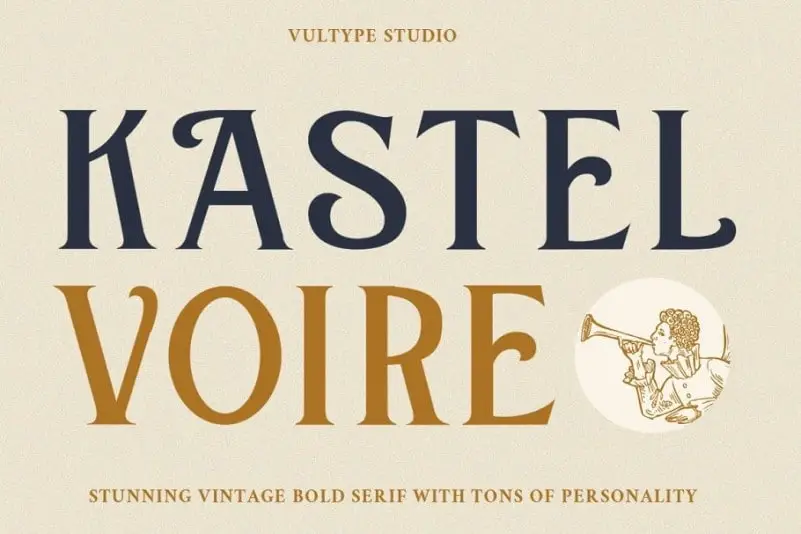
Kastel Voire Serif Font – Download Grátis
A Kastel Voire Serif é uma fonte serif display moderna que se destaca perfeitamente para criações visuais como logomarcas, identidades corporativas e cabeçalhos de sites. Com sua aparência minimalista e contrastes sutis, essa font foi projetada pela Vultype Co. e inspirou-se na estética da moda ao longo das décadas últimas décadas. A Kastel Voire Serif é uma combinação perfeita entre o modernismo e a nostalgia, tornando-a ideal para uso em logomarcas, masthead’s e citações-chave. Esta font se adapta harmoniosamente com uma fonte sans-serif minimalista ou script leve, criando um conjunto de design elegante que é certo para fazer sua marca soar única e sofisticada no mundo digital.